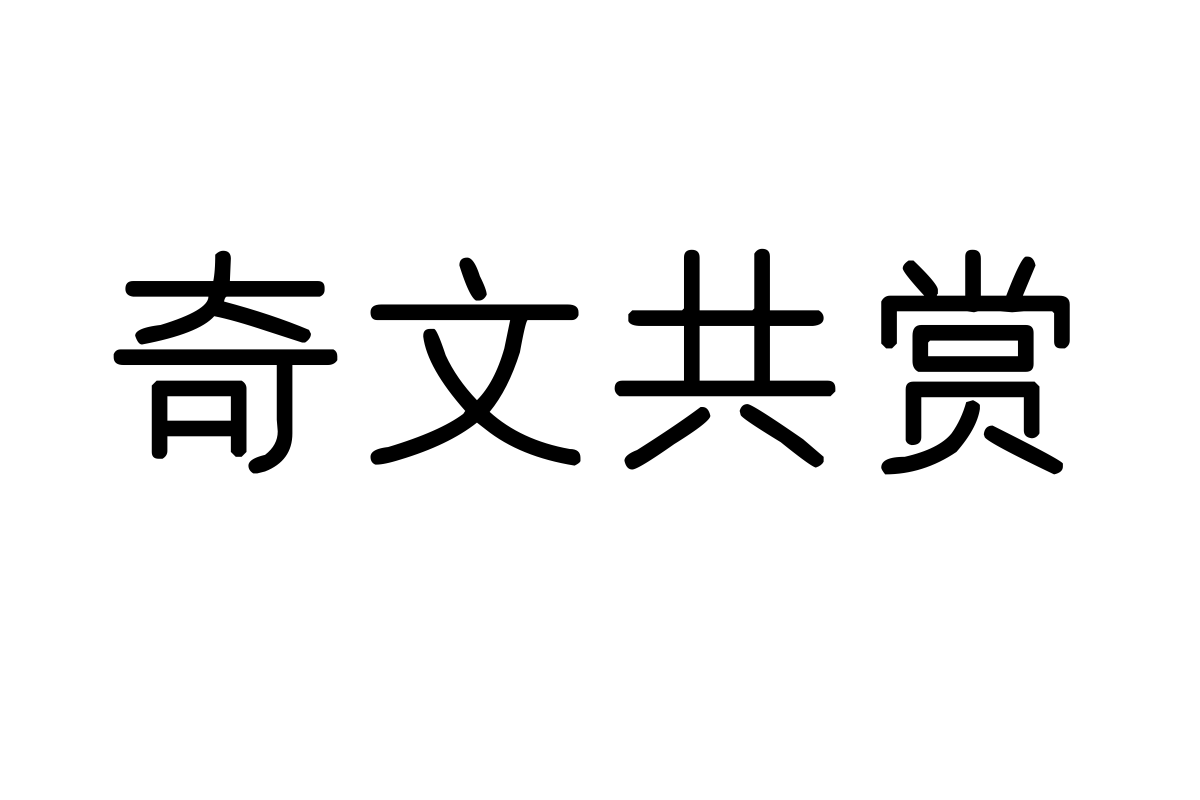
汉标中圆体字体是一款具有独特风格的中文字体,它采用了圆润的字形设计,给人以柔和、亲切的感觉。这种字体的特点是笔画圆润饱满,结构简洁明了,适合用于需要传达温馨、亲切氛围的场合。
汉标中圆体字体适用于各种印刷品和数字媒体,如书籍、杂志、报纸、广告、网站等。它的应用范围非常广泛,无论是在商业还是日常生活中,都可以通过使用这款字体来提升整体的视觉效果和审美体验。